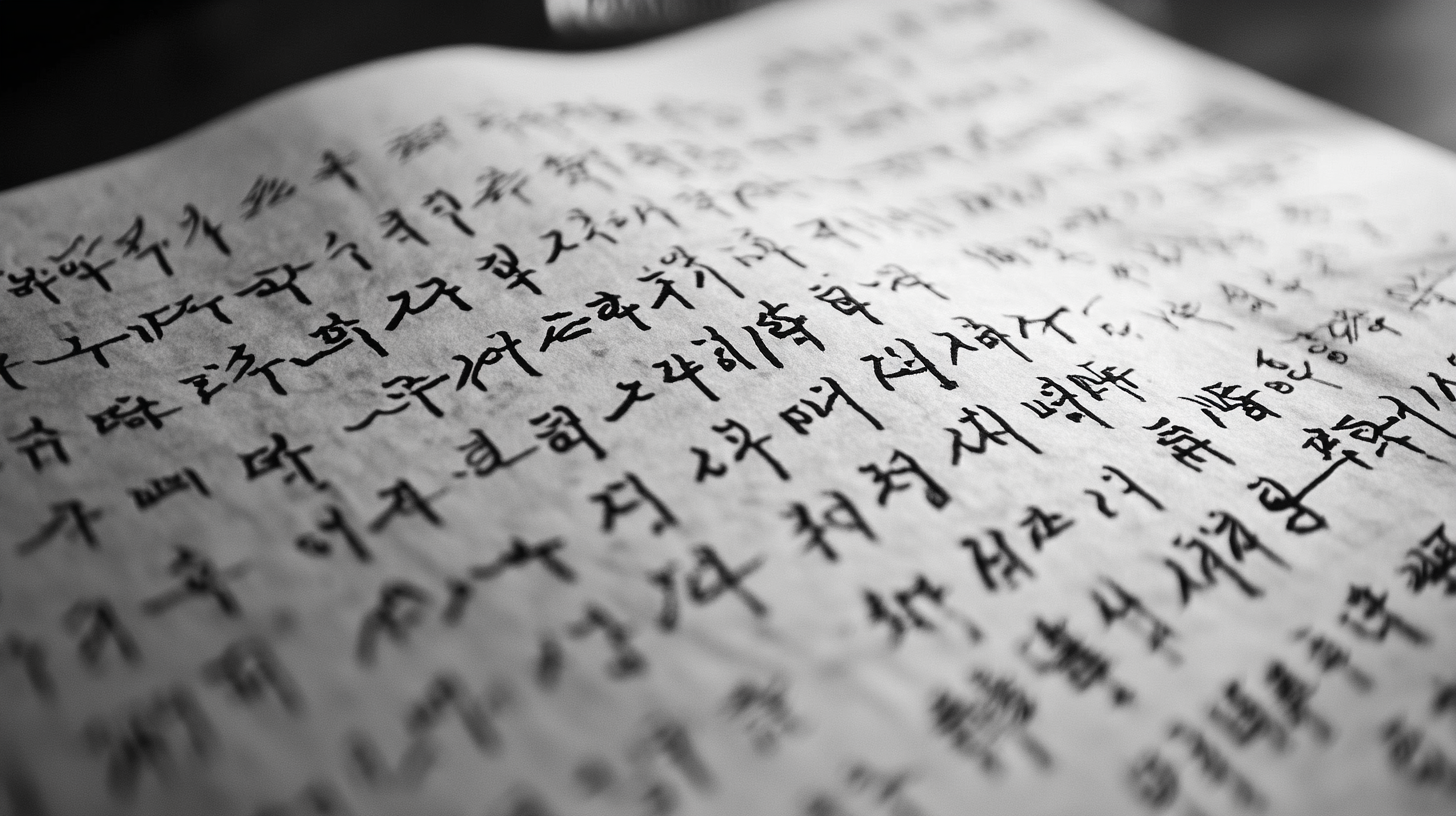
명필이 되는 가장 빠른 방법이 있을까요? 🤔 물론 글씨 교정은 하루아침에 완성되지 않지만, 올바른 방법을 따르면 훨씬 빠르게 개선할 수 있어요! ✨
오늘은 단기간에 글씨를 예쁘게 바꾸는 비법을 알려드릴게요. 기본 원칙과 실전 연습법을 제대로 익히면 여러분도 명필로 거듭날 수 있어요! 😊
⏳ 글씨 교정, 얼마나 걸릴까?
"글씨 교정을 하면 얼마나 걸릴까요?" 이 질문은 많은 분들이 궁금해하는 부분이에요. 🤔 사실 글씨 교정에 걸리는 시간은 개인 차이가 있지만, 올바른 방법으로 연습하면 2~4주 안에 확실한 변화를 볼 수 있어요! ✨
다만, 꾸준한 연습이 필수예요. 하루 10~30분 정도 집중적으로 연습한다면 한 달 안에 눈에 띄게 정돈된 글씨를 가질 수 있어요! 🖊
📊 글씨 교정 예상 기간
연습 기간 변화 추천 연습법 1주 차 획이 정리되고 필기 속도가 안정됨 기본 획 연습 & 모눈 노트 사용 2~3주 차 글자 크기와 자간이 균형 잡힘 필사 연습 & 속도 조절 훈련 4주 차 자연스러운 필체 완성 개인 필체 스타일 확립 이처럼 단계별로 훈련하면 빠른 시간 안에 글씨를 교정할 수 있어요. 그렇다면, 빠르게 글씨를 교정하는 핵심 원칙은 무엇일까요? 🤔
🚀 빠르게 글씨 교정하는 핵심 원칙
글씨를 빨리 교정하고 싶다면 무작정 많이 쓰기보다 올바른 연습법을 따르는 것이 중요해요! ✍ 몇 가지 핵심 원칙만 제대로 지켜도 단기간에 눈에 띄는 변화를 만들 수 있어요. 😊
잘못된 필기 습관을 그대로 유지한 채 연습을 반복하면 오히려 교정이 더 어려워질 수 있어요. 지금부터 효과적으로 글씨를 교정하는 5가지 핵심 원칙을 알려드릴게요! 🔥
📌 빠른 글씨 교정을 위한 5가지 원칙
원칙 설명 효과 ✏ 올바른 필기 자세 유지 연필을 너무 꽉 쥐지 않고, 손목과 어깨에 힘을 빼기 손의 피로 감소 & 필기 안정성 증가 📏 글씨 크기와 간격 맞추기 모눈 종이를 사용하여 일정한 크기로 연습 균형 잡힌 글씨체 형성 📝 기본 획 연습부터 시작 직선, 곡선, 대각선 획을 반복적으로 연습 획이 깨끗하고 일정해짐 ⌛ 필기 속도 조절 처음엔 천천히 쓰고 점차 속도를 올리기 흐트러지지 않는 필체 완성 📖 필사 연습 활용 좋아하는 문장을 따라 쓰며 자연스러운 글씨체 익히기 획의 유연성 증가 & 개성 있는 필체 형성 위 5가지 원칙을 지키면서 연습하면 훨씬 빠르게 글씨 교정이 가능해요! 😊 그렇다면, 실전에서 효과적인 3단계 훈련법은 무엇일까요? 다음 섹션에서 함께 알아볼게요! 🚀
🏆 글씨 교정을 위한 3단계 훈련법
글씨를 빠르고 정확하게 교정하려면 체계적인 연습 방법을 따르는 것이 중요해요. ✍ 기본기 → 패턴 연습 → 응용 필기 이 3단계 훈련법을 실천하면 효과적으로 글씨를 개선할 수 있어요! 😊
많은 사람들이 글씨를 교정할 때 바로 문장을 따라 쓰려고 하지만, 올바른 획 연습부터 차근차근 진행하는 것이 더 효과적이에요! 🚀
📌 3단계 글씨 교정 훈련법
훈련 단계 설명 효과 1단계: 기본기 훈련 직선, 곡선, 원형, 대각선 획을 반복 연습 획이 균형 잡히고 필압이 안정됨 2단계: 패턴 연습 자주 쓰는 글자 패턴을 반복해서 연습 획의 일관성과 가독성 향상 3단계: 응용 필기 책 속 문장이나 명언을 필사하며 실전 적용 자연스러운 글씨체 완성 이 3단계를 순서대로 연습하면 획이 정리되고, 더 빠르게 명필이 될 수 있어요! 😊 그렇다면 어떤 필기구를 사용해야 효과적인 연습이 가능할까요? 다음에서 알아볼게요! ✏
✏ 효과적인 필기 도구 선택법
글씨 교정에 있어서 필기구 선택은 매우 중요해요! ✍ 올바른 필기구를 사용하면 획의 균형을 맞추고 필기감을 조절하는 데 도움이 돼요. 😊
하지만 연필, 볼펜, 만년필 등 다양한 필기구 중 어떤 걸 사용해야 할지 고민될 때가 많아요. 그래서 오늘은 글씨 교정에 가장 적합한 필기구를 추천해드릴게요! 🔍
📌 글씨 교정에 적합한 필기구 비교
필기구 특징 추천 용도 ✏ 2B 연필 적당한 필압 조절 가능, 부드러운 필기감 초보자, 기본 획 연습 🖊 유성 볼펜 필기감이 부드럽고 선명한 글씨 표현 가능 속도 조절 연습, 실전 필기 🖋 만년필 획의 굵기 조절 가능, 필압에 따라 다양한 표현 가능 획의 흐름 연습, 고급 필기체 🖍 그립 보조 연필 손가락 위치 교정, 올바른 필기 습관 형성 어린이, 악필 교정 초보자 필기구를 선택할 때는 자신의 필기 스타일과 연습 목표에 맞춰서 선택하는 것이 중요해요! 😊 그렇다면, 매일 10분씩 꾸준히 연습할 수 있는 실전 글씨 교정 루틴은 어떻게 만들까요? 🤔
⏰ 매일 10분! 실전 글씨 교정 루틴
바쁜 일상 속에서도 매일 10분만 투자하면 글씨체를 충분히 교정할 수 있어요! ✍ 짧은 시간 동안 집중적으로 연습하는 것이 핵심이에요. 😊
아래의 10분 루틴을 따라 하면 효율적으로 글씨 교정을 할 수 있어요. 꾸준히 실천하면 한 달 후에는 확연히 달라진 필체를 확인할 수 있을 거예요! 🚀
📌 하루 10분 글씨 교정 루틴
시간 연습 내용 효과 1~3분 기본 획 연습 (직선, 곡선, 대각선) 획의 균형과 필압 조절 능력 향상 4~6분 자주 쓰는 단어 연습 (예: "한글", "사랑") 실전 필기 연습 & 글자 배열 정리 7~9분 짧은 문장 필사 연습 자연스러운 필기 흐름 익히기 마지막 1분 오늘 연습한 글씨 비교 & 개선점 체크 자기 피드백 & 꾸준한 발전 이 루틴을 매일 실천하면 한 달 뒤에는 글씨체가 눈에 띄게 정돈될 거예요! 😊 하지만 중요한 것은 꾸준함이에요. 꾸준함이 어떻게 명필로 이어지는지 다음 섹션에서 알아볼게요! ✨
🔥 꾸준함이 답! 명필이 되는 습관
어떤 연습법도 꾸준함이 없다면 효과를 볼 수 없어요! 명필이 되는 가장 확실한 방법은 매일 조금씩 연습하는 것이에요. ✍ 하루에 10~15분씩만 연습해도 한 달 후면 확실한 변화를 느낄 수 있어요! 😊
특히 글씨 교정은 단순히 글을 많이 쓰는 것이 아니라 올바른 필기 습관을 유지하는 것이 중요해요. 아래에서 꾸준히 연습할 수 있는 실천법을 소개해드릴게요! 🚀
📌 명필이 되기 위한 5가지 습관
습관 설명 효과 ✍ 하루 10~15분 연습 기본 획, 단어, 문장 필사를 매일 연습 꾸준한 교정 효과 & 자연스러운 필체 완성 📖 필사 습관 만들기 좋아하는 책이나 명언을 따라 쓰기 손글씨 감각 향상 & 글씨체 안정 📏 일정한 글씨 크기 유지 모눈 종이나 가이드라인 활용 균형 잡힌 글씨체 형성 ✋ 손 스트레칭 & 필기 자세 점검 손목 유연성 운동 & 올바른 필기 습관 유지 손 피로 감소 & 장시간 필기 가능 📅 목표 설정 & 글씨 비교 일주일 단위로 글씨 변화를 체크 점진적인 발전 확인 & 동기 부여 꾸준히 연습하고 변화 과정을 기록하면 더 큰 동기 부여가 될 수 있어요! 😊 이제 글씨 교정과 관련된 궁금증을 FAQ에서 해결해볼까요? ✨
Q1. 글씨 교정은 얼마나 해야 효과를 볼 수 있나요?
A1. 하루 10~15분씩 꾸준히 연습하면 보통 2~4주 안에 눈에 띄는 변화를 볼 수 있어요. 하지만 완전히 습관화하려면 최소 2~3개월 동안 연습하는 것이 가장 효과적이에요! ✍
Q2. 글씨를 바르게 쓰려면 어떤 필기구를 사용하는 것이 좋을까요?
A2. 초보자는 2B 연필이나 유성 볼펜이 좋아요. 획을 부드럽게 조절할 수 있고, 필기 압력을 쉽게 조절할 수 있기 때문이에요! ✏
Q3. 모눈 종이를 사용하면 글씨 교정에 도움이 되나요?
A3. 네! 📏 모눈 종이는 글자 크기와 간격을 일정하게 유지하는 데 큰 도움이 돼요. 특히 글씨 크기가 일정하지 않거나 삐뚤어지는 분들에게 추천해요!
Q4. 글씨 속도를 너무 늦추면 필기할 때 불편하지 않나요?
A4. 처음에는 천천히 연습하는 것이 중요해요. 정확한 획과 균형을 익힌 후 점점 속도를 높이면 빠르게 써도 글씨체가 망가지지 않아요! 🚀
Q5. 악필을 완전히 교정할 수 있을까요?
A5. 네, 가능합니다! 😊 악필도 올바른 연습과 습관을 들이면 충분히 개선할 수 있어요. 특히 기본 획 연습 + 필사 연습을 병행하면 효과적이에요!
Q6. 글씨 교정을 위해 하루에 몇 분 정도 연습하는 게 좋나요?
A6. 하루 10~15분 정도면 충분해요! ⏰ 짧더라도 매일 꾸준히 연습하는 것이 가장 중요한 포인트예요. 💪
Q7. 손에 힘을 너무 빼면 글씨가 흔들리는데 어떻게 해야 하나요?
A7. 손을 너무 힘없이 쓰면 글씨가 불안정해질 수 있어요. 적당한 힘을 주고, 손목과 팔 전체를 이용해 부드럽게 필기하는 연습을 해보세요! ✋
Q8. 글씨 교정을 도와주는 어플이나 도구가 있나요?
A8. 네! 📱 GoodNotes, Noteshelf 같은 디지털 필기 앱을 활용하면 손글씨를 연습할 수 있어요. 또한, 글씨 교정 워크북이나 필기 가이드 종이를 활용하면 더욱 효과적이에요!
이제 명필이 되는 방법을 모두 알아봤어요! 오늘부터 꾸준히 연습해서 나만의 예쁜 글씨체를 완성해보세요! ✨